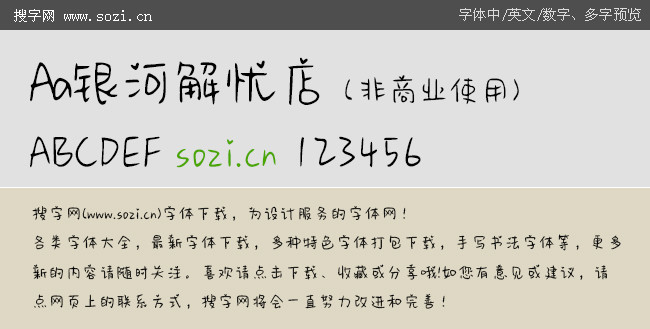
Aa銀河解憂店
搜字網(wǎng)給大家提供一款A(yù)a銀河解憂店(非商業(yè)使用)中文字體下載,該字體是一款手寫(xiě)風(fēng)格的卡通字體,字體筆觸適中,書(shū)寫(xiě)灑脫,以心形圖案進(jìn)行點(diǎn)綴,具有很好的視覺(jué)感,適用于平面宣傳設(shè)計(jì)、網(wǎng)頁(yè)設(shè)計(jì)、海報(bào)設(shè)計(jì)等應(yīng)用(此字體為個(gè)人非商用版,商用可以聯(lián)系QQ:1006760504)。